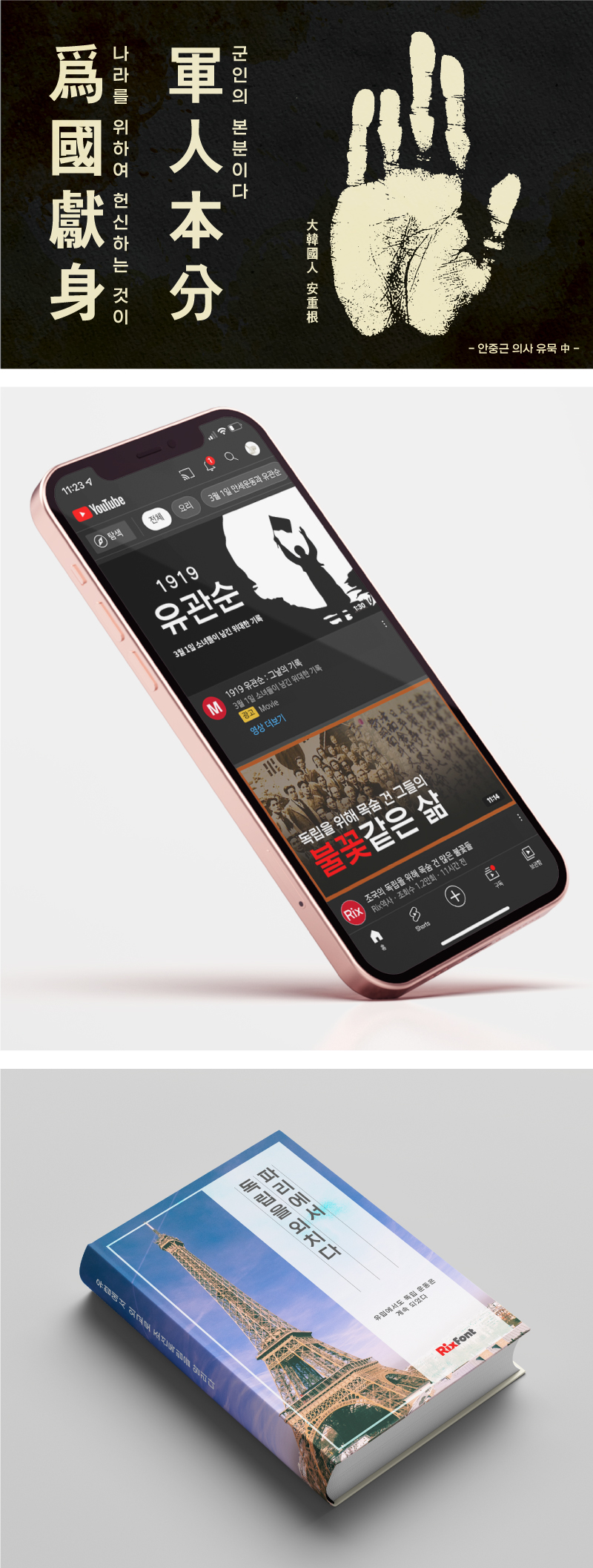
개화기의 시대적 분위기를 담은 강인하고 힘 있는 서체 독립돋움의 Special Edition입니다.
Rix독립고딕SE는 꽉 찬 네모꼴에 두껍고 단단한 획, 절제된 표현과 간결한 직선의 형태에서 모던함이 돋보이며, Rix독립돋움SE는 손글씨의 획을 적용한 자소 디자인과 꽉 찬 골격의 넓은 폭으로 좀 더 예스러운 느낌이 강조되었습니다.
공간적인 비율과 사용성을 고려하여 추가 파생한 웨이트로 활용도를 높였습니다.